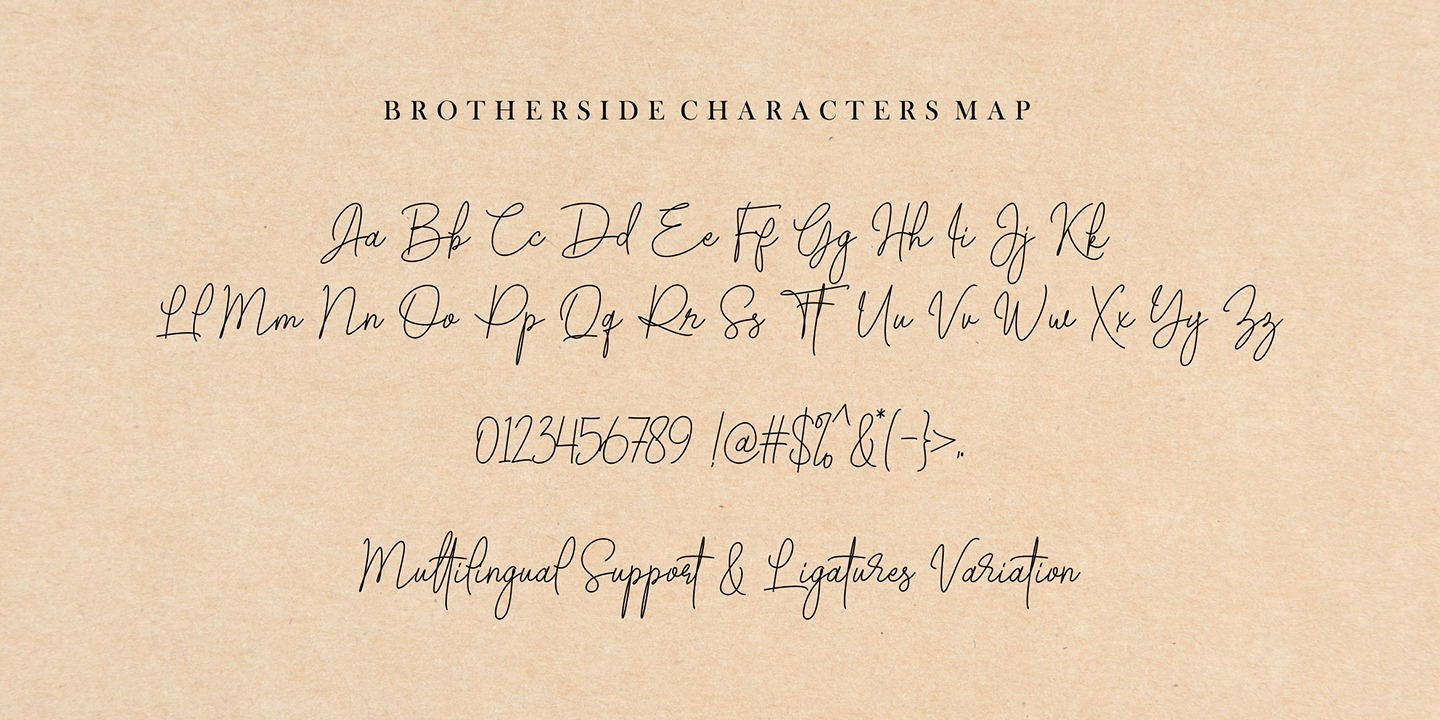
Tác giả: Figuree Studio​
Phân loại: Thanh lịch
Kiểu chữ: Chữ ký (Signature)
Font 1FTV Brotherside Signature là một kiểu chữ viết tay đầy phong cách, font chữ này thuộc bộ font 1FTV mang đậm dấu ấn cá nhân và sự tinh tế. Với các nét chữ mượt mà, uyển chuyển như chữ ký, font này rất phù hợp cho các thiết kế mang tính nghệ thuật và sang trọng, chẳng hạn như logo thương hiệu, thiệp mời, hoặc các sản phẩm cao cấp. Font 1FTV Brotherside Signature không chỉ tạo cảm giác độc đáo, thanh lịch mà còn thể hiện sự tinh tế và chuyên nghiệp, giúp các dự án thiết kế nổi bật với nét cá nhân hóa và đẳng cấp riêng.
Font 1FTV Brotherside Signature mang đường nét uyển chuyển